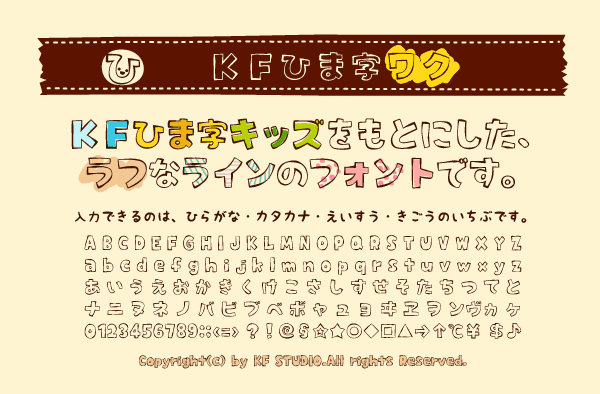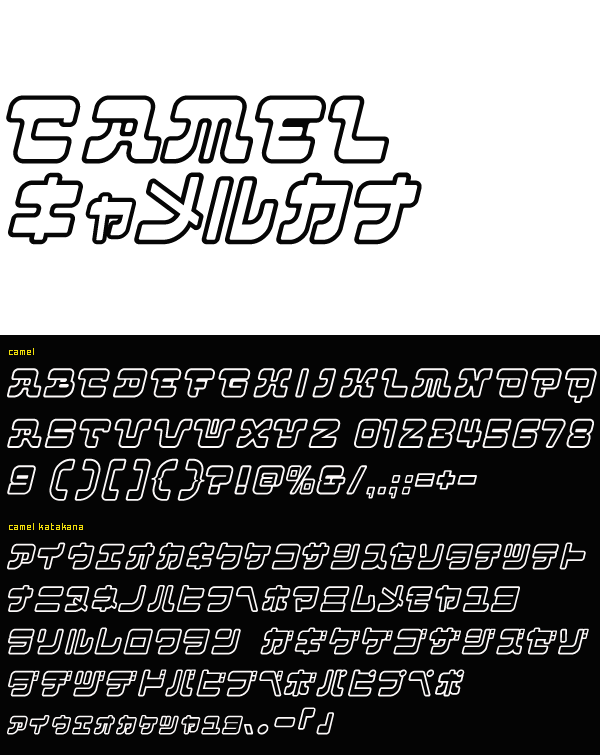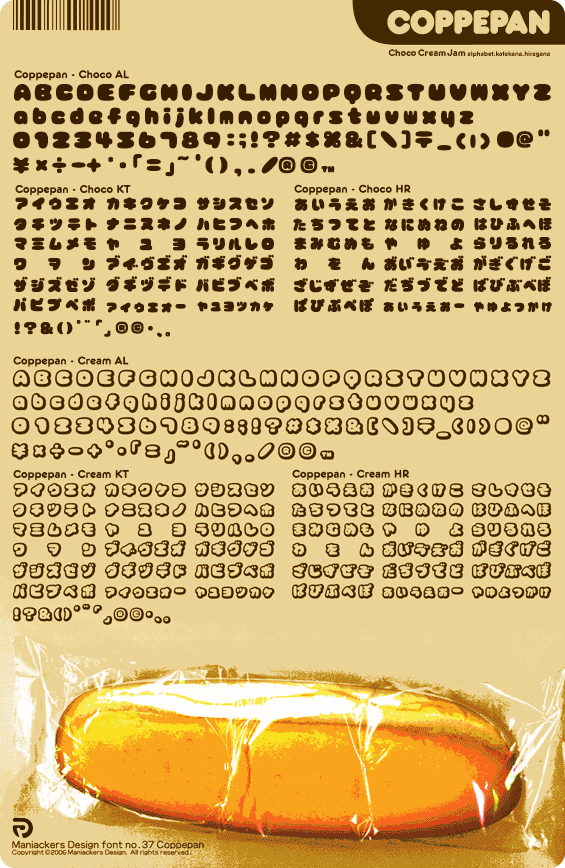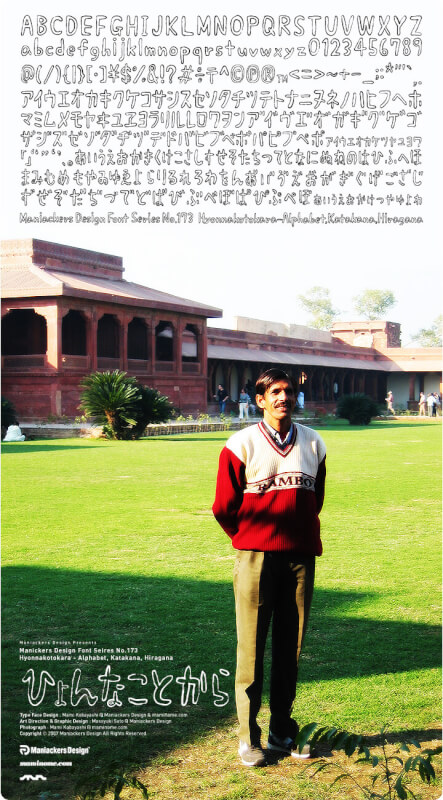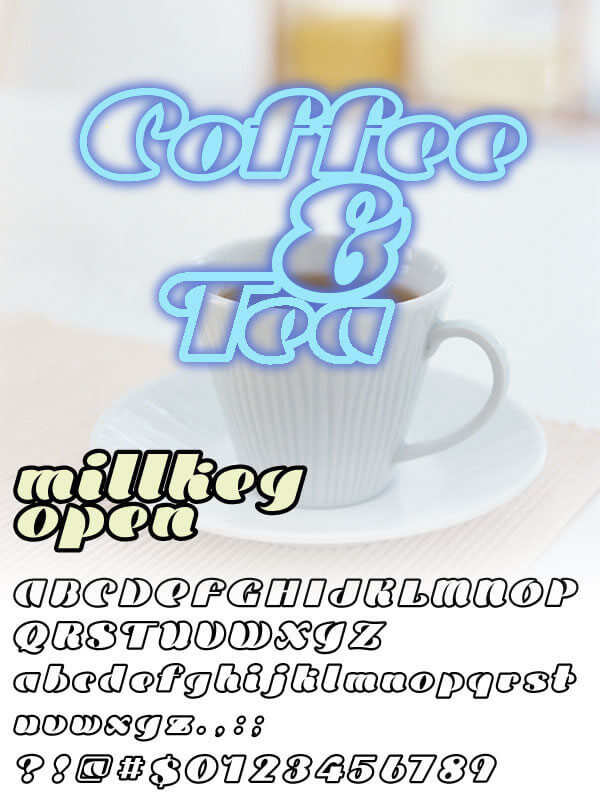
フリーダウンロード可能な縁取りフォント32個
フォントの背景は透明、文字の周りに1pxほどのラインで囲まれた縁取りフォントを紹介します。中にはデフォルトで縁取られていないフォントもございます。その場合はアイキャッチでイメージしていただき、フォトショップなどのグラフィックソフトで加工してください。
AK-cookies vanilla
クッキーみたいなフォント。チョコ(黒塗り)とバニラ(白抜き)の2書体。
Automatic
頭がトンガった部分がチャームポイントの斜体フォント。
Camel open AL&kana
特徴的な字形のカナ・英数字フォント。商用利用にはロイヤリティフリーの「CFONT COLLECTION」を購入する必要あり。
Chape 02 AL_kana
文字の端にいくほど細くなるフォント。商用利用にはロイヤリティフリーの「CFONT COLLECTION」を購入する必要あり。
CHUBBY
カクカクとしたプロポーショナルフォント。大文字で打つと黒塗り、小文字で打つと白抜きの文字。
Cliper open kana
2バイトのカタカナフォント。商用利用にはロイヤリティフリーの「CFONT COLLECTION」を購入する必要あり。
Cliper Series
文字の中の●(黒丸)が特徴的なフォント。商用利用にはロイヤリティフリーの「CFONT COLLECTION」を購入する必要あり。
Cliper shadow kana
影付きのカタカナフォント。商用利用にはロイヤリティフリーの「CFONT COLLECTION」を購入する必要あり。
Coppepan-AL, KT, HR
食べたくなってしまうような美味しそうなフォントを!と考えられた極太で丸々としたフォント。
coro edge
coro(コロ)のふちどりバージョンフォント。
Hyonnakotokara-AL, KT, HR
鉛筆で下書きしたようなフォント。
Kakomi-A
かこみ系フォント。
Kakomi-B
かこみ系フォント。
Kakomi-C
かこみ系フォント。
KFひま字ワク
「KFひま字キッズ」を元にした、ラフなラインの白抜きフォント。
Mikiyu Font Mokomori-A
手書き風の白抜き文字フォント。アルファベット、数字、記号のみ。
Millkey Open
ミルキーのような字体。商用利用にはロイヤリティフリーの「CFONT COLLECTION」を購入する必要あり。